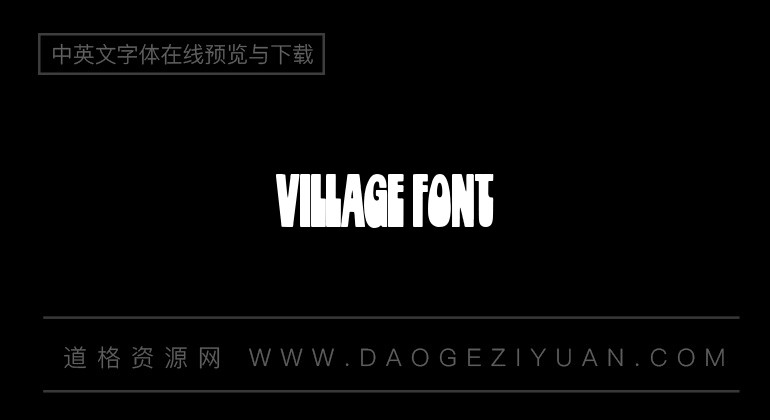
Village Font是一种老式风格的字体,看起来非常古朴和传统。它的设计灵感来源于历史上的手写字母和手工雕刻文字,给人以历史感和温暖的感觉。这种字体通常用于书籍、海报、商标和其他需要表达传统、稳健、和历史感的设计项目中。它的字母形状粗壮,线条粗犷,字母之间的间距较小,看起来非常有力和有冲击力。如果您需要一种具有传统气息而又不失现代感的字体,那么Village Font可能是一个不错的选择。内容介绍
Village Font是一款非常不错的手写艺术字体,具有很好的视觉感,适合于文化类的宣传设计、商业类品牌的广告和产品包装设计以及个性化文字排版等较多场景。